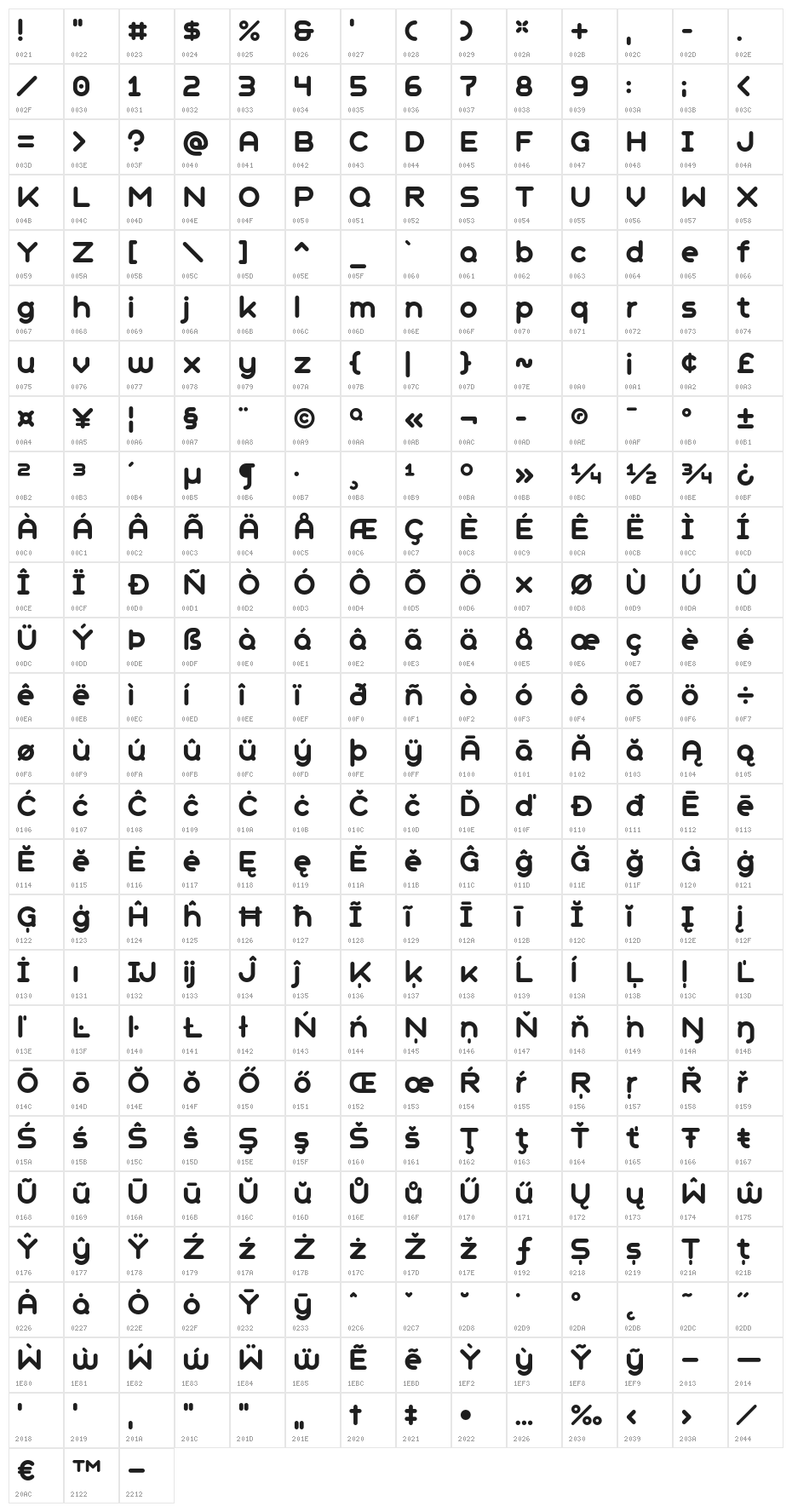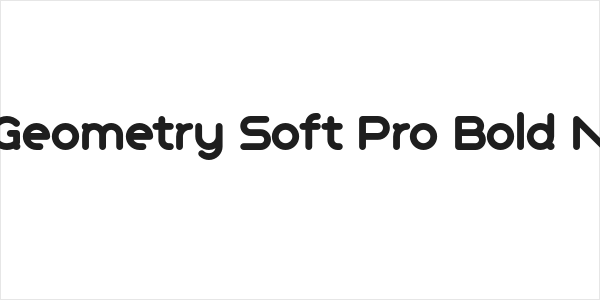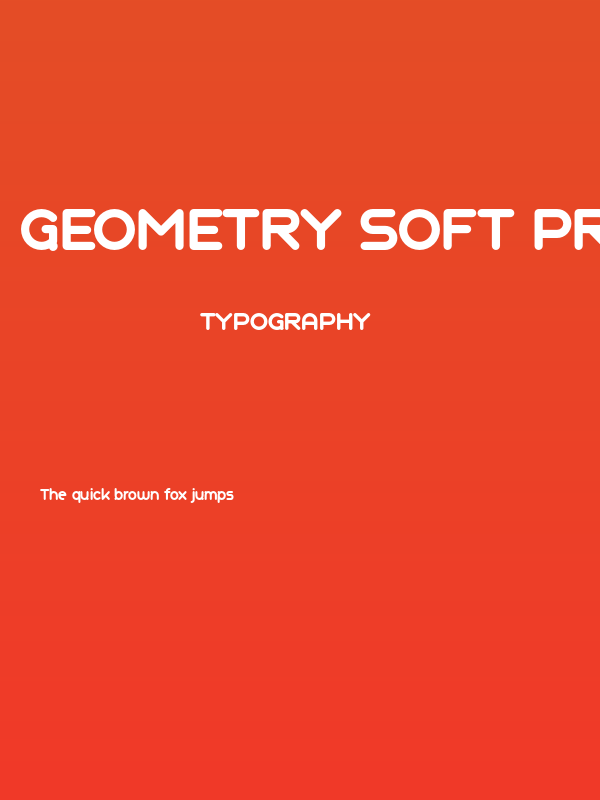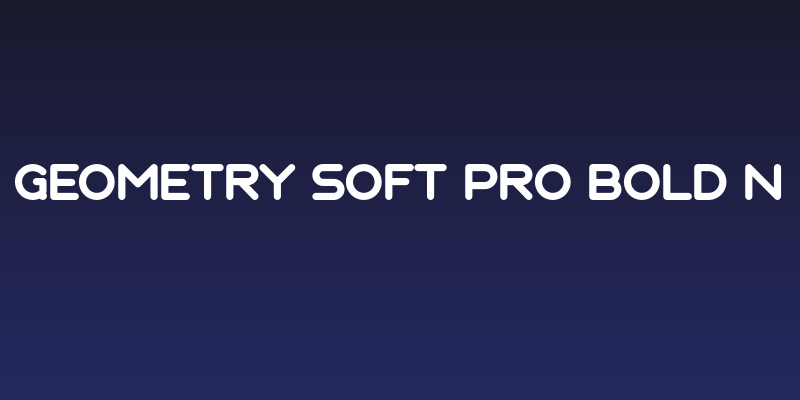
Geometry Soft Pro Bold N Font
✎ Round
| 分类 | Round |
| 使用场景 | Headlines, Logos, Branding |
| 推荐项目 | Ideal for branding, logos, headlines, and packaging design where a modern and friendly appearance is desired. |